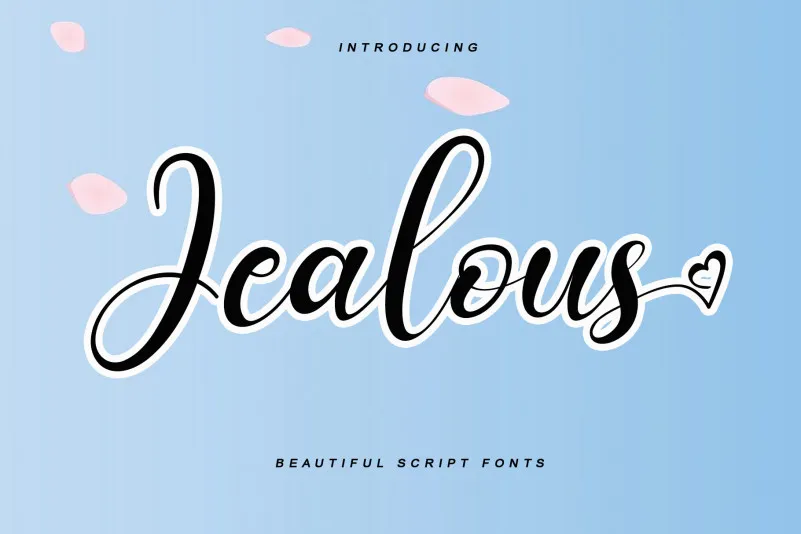
A fonte Jealous é uma escolha perfeita para quem busca um design elegante e detalhado. Esta script font foi meticulosamente criada por KateEngciu, tornando-a atraente tanto no aspecto quanto no conteúdo. O fato de ser PUA (Propriedade de Uso Ávido) codificada significa que você terá facilidade em acessar todos os caracteres e swashes, permitindo uma ampliação sem limites do seu design. Ideal para criações que requerem um ar refinado e sofisticado, Jealous é a escolha perfeita para designers de jogos, ilustradores ou qualquer profissional buscando uma fonte de alta qualidade para suas obras. Quebre as barreiras da monotonia com Jealous, uma fonte única e impressionante que será um recurso valioso em seu arsenal de design.